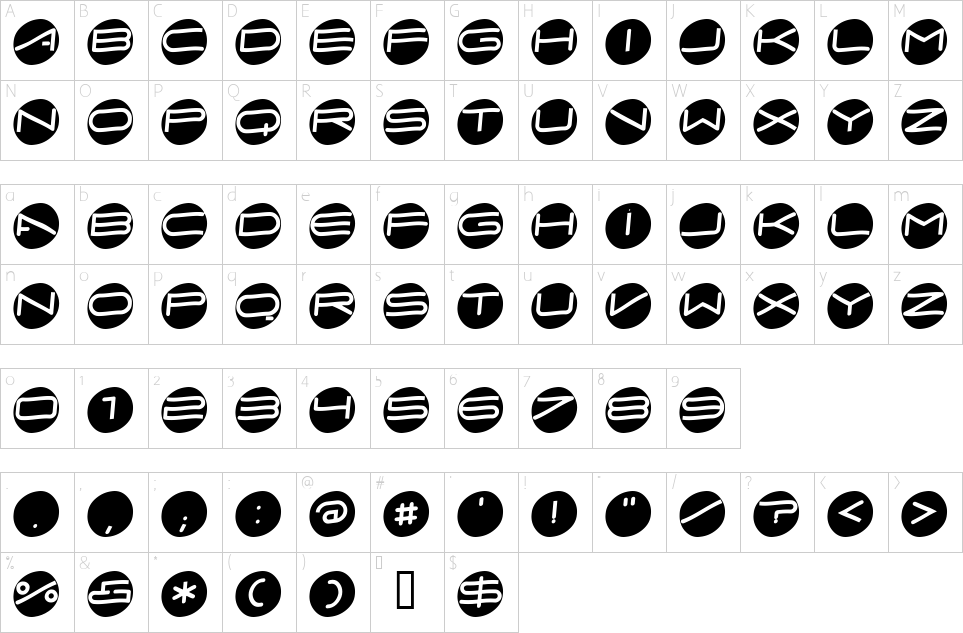
A fonte ABCari é uma escolha perfeita para quem procura um estilo elegante e moderno em seus projetos de design. Desenvolvida pelo designer Manfred Klein Wen, ABCari se destaca pela sua tipografia curvilínea e fácil de ler, que se adapta perfeitamente a uma ampla gama de aplicações, como websites, gráficos e materiais de impressão. Com um design único e moderno, ABCari é uma excelente opção para quem busca uma fonte moderna e atraente, sem comprometer a legibilidade. Se você está procurando por uma fonte grata para uso pessoal ou profissional, ABCari é uma ótima opção para suas necessidades.